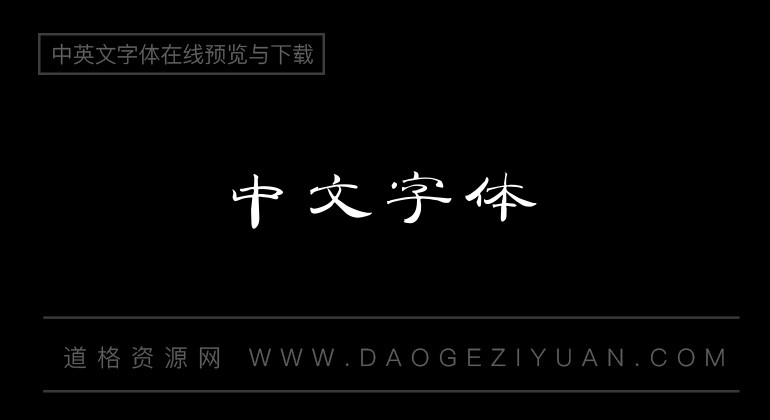
腾祥范笑歌简牍简
腾祥范笑歌简牍简是一款楷书字体,由腾祥范字体设计师潘忠振设计,属于汉字楷书字体的一种,也是一款现代楷书字体。腾祥范笑歌简牍简设计精美,有着清新、活泼的特点,笔画流畅,弯曲细腻,字形端庄大方,非常适合用于书法、绘画、印刷等多种应用场景,具有较高的美学价值。
腾祥范笑歌简牍简是一款非常不错的手写艺术字体,具有很好的视觉感,适合于文化类的宣传设计、商业类品牌的广告和产品包装设计以及个性化文字排版等较多场景。